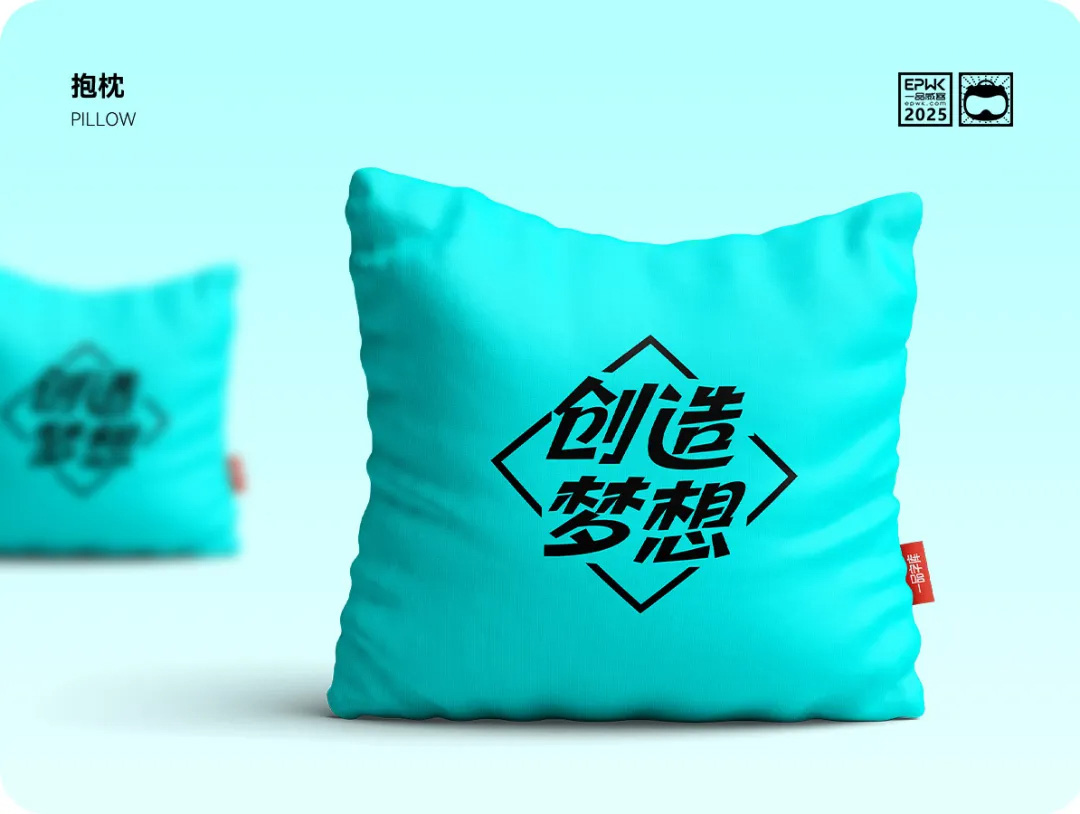
一品启航体
一品启航体,这款字体结构工整、笔画清晰,兼顾美观与易读性,适用于标题、正文、海报、包装、LOGO 等多种场景。字形优雅稳定,风格百搭耐看,适配日常排版与创意设计,让文字呈现更舒适、更具质感。一品启航体一笔一画,皆是细节,以均衡的比例、流畅的线条打造舒适视觉体验,字形端正大气,风格简约现代。无论是商业设计、品牌宣传还是日常排版,都能轻松驾驭,让文字更有格调与力量。一品启航体字体下载。
整体字形呈平行四边形外框结构,通过倾斜的视觉轴线赋予字体强烈的方向感与动势,既呼应了"启航"主题的进取精神,又打破了传统字体的静态平衡,营造出充满活力与现代感的视觉表现力。
“一品启航体”以中国传统书法为根基,融入现代设计美学,字形遒劲昂扬,笔锋充满动势,象征着一品威客锐意进取、勇立潮头的品牌内核。作为公益字体,其将广泛应用于文化传播、公益宣传、商业设计等领域,旨在成为连接你我、传递正能量的桥梁,激励更多人勇敢追梦,共创美好未来。
设计亮点:传统与现代交融
梦想、青春、创意,是“一品启航体”的标签。作为一品威客纳斯达克上市纪念公益字体,其在字形特征、字形结构、笔画设计等方面呈现诸多亮点,体现了传统与现代的交融。
中宫舒展,识别度高。字体采用中宫舒展设计,扩大字面率,兼具传统书法结构美学与现代阅读习惯,视觉张力与辨识度并存。
动感外框,刚柔并济。平行四边形外框赋予字体强烈方向感,呼应“启航”主题;笔画转折处巧妙融入弧度,刚毅中透出温度,传递企业“锐意进取中不失人文关怀”的理念。
动态笔触,灵动鲜活。模拟真实书写压感,线条粗细变化自然,断笔处理营造呼吸韵律,打破传统字体静态平衡,展现品牌开放发展的创新基因。